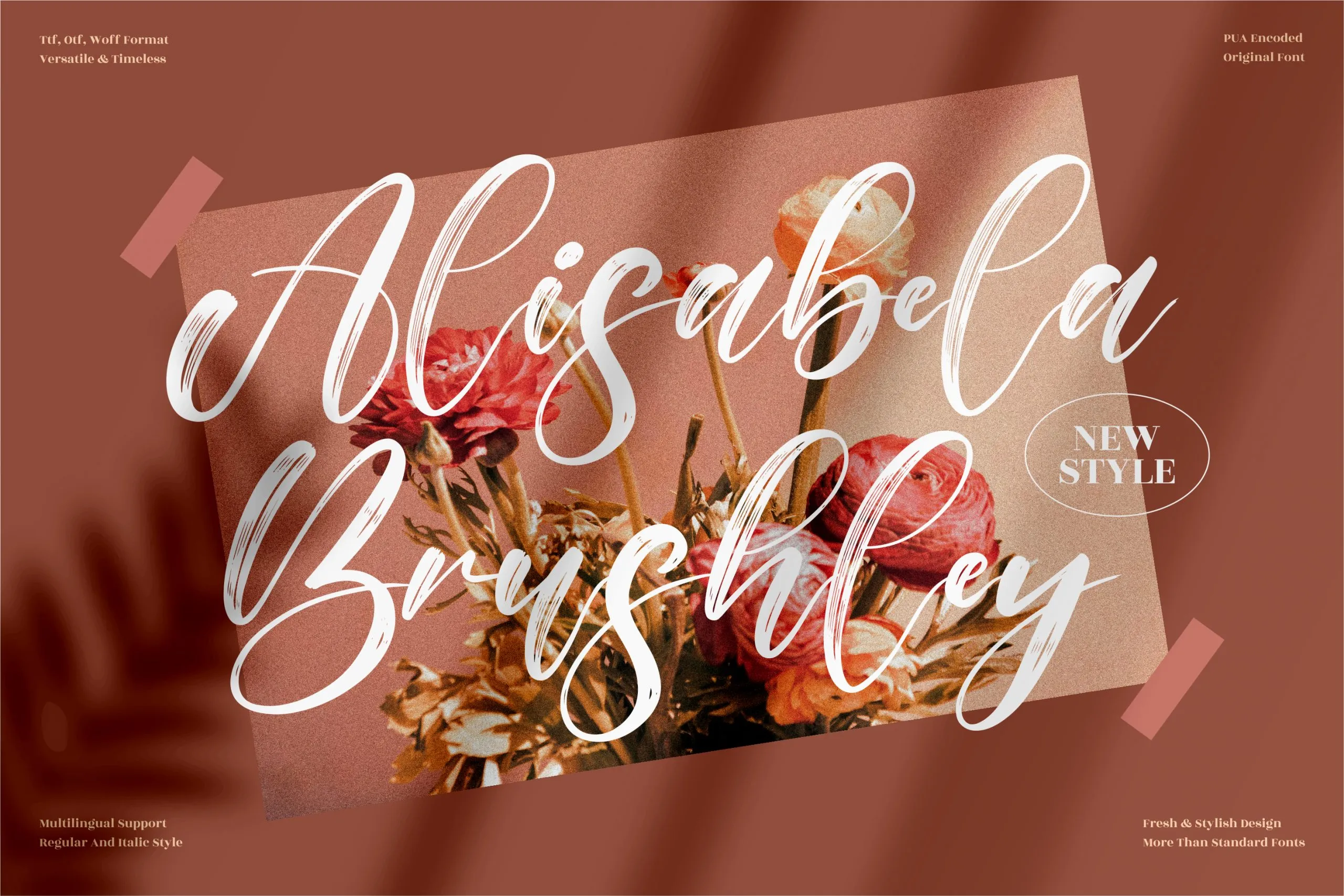
Alisabela Brushley Font – Fonte Grátis
Alisabela Brushley Font
A Alisabela Brushley Font é uma elegante seleção de letras cursivas projetada para enriquecer qualquer projeto visual com sua delicadeza única. Este tipo de letra, feito à mão, se adapta perfeitamente a uma variedade impressionante de aplicações. Seja para criar logotipos e marcas, desenhar objetos de casa, embalagens de produtos, ou até mesmo um cartão de nome impresso, a Alisabela Brushley é sua fonte ideal. Os seus traços suaves e delicados fazem-a perfeitamente adequada para ambientes como mugs com café da manhã, slogans em placas de rua, postais personalizados, rótulos em embalagens de produtos e até mesmo um apagado para a foto de uma celebração especial. Além disso, ela oferece uma opção incrível para aqueles projetos luxuosos que exigem um toque autêntico e pessoal. Com design sofisticado e detalhes meticulosamente criados pelo designer perspectype, é claro que a Alisabela Brushley Font não apenas oferecerá o acabamento perfeito para qualquer projeto da sua lista, mas também trará à vida suas criações de maneira única.